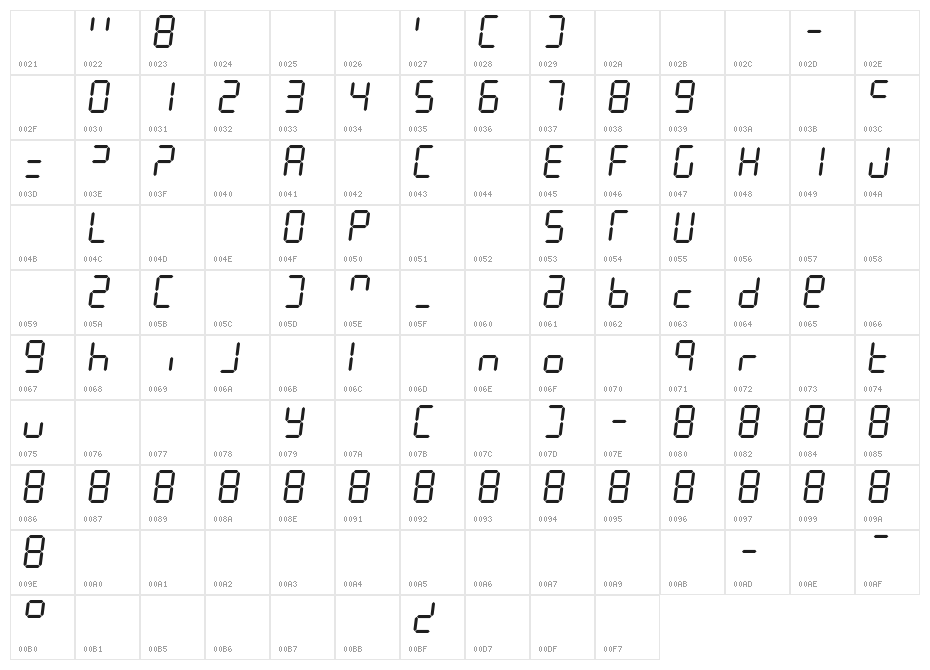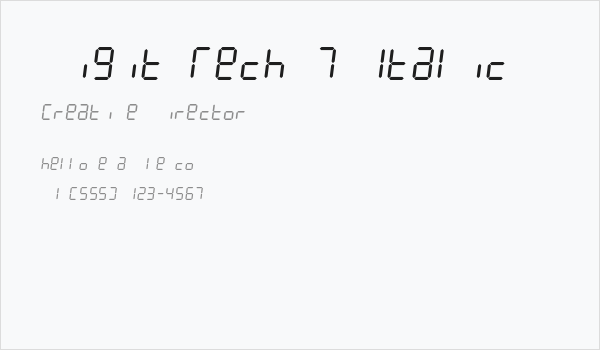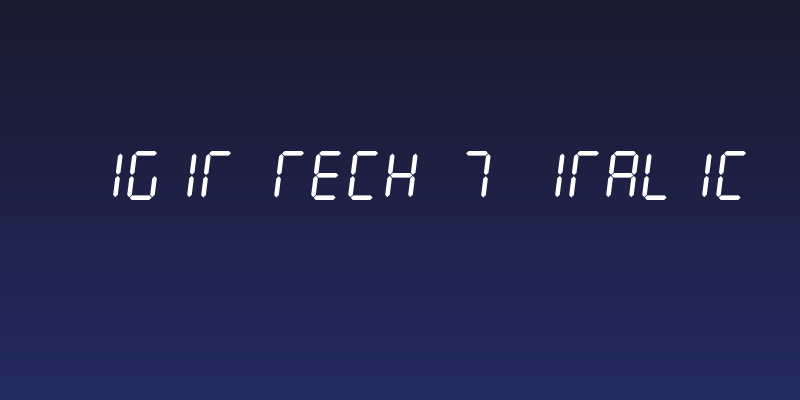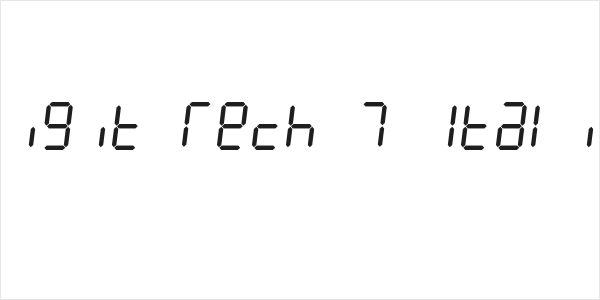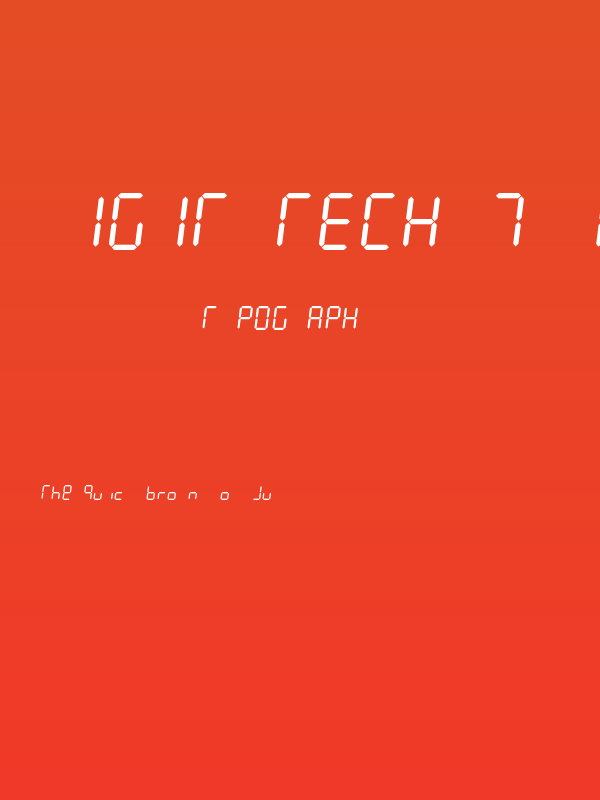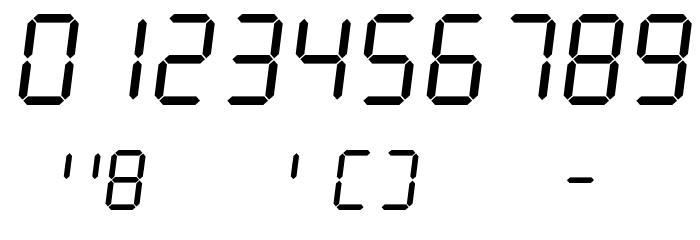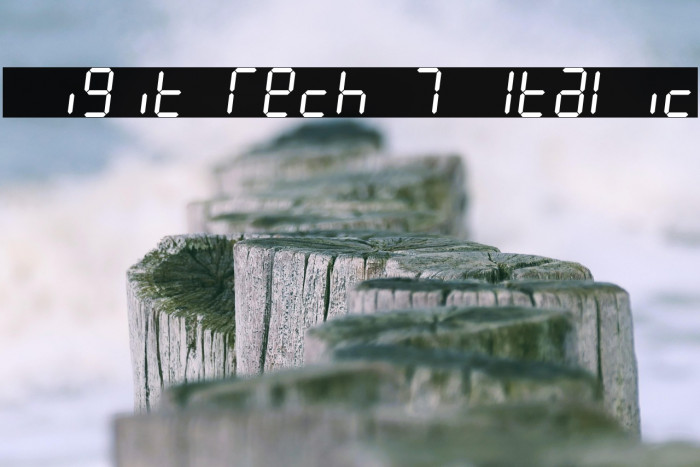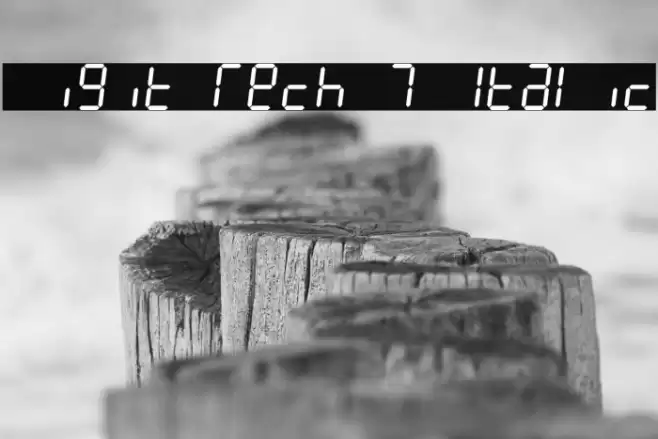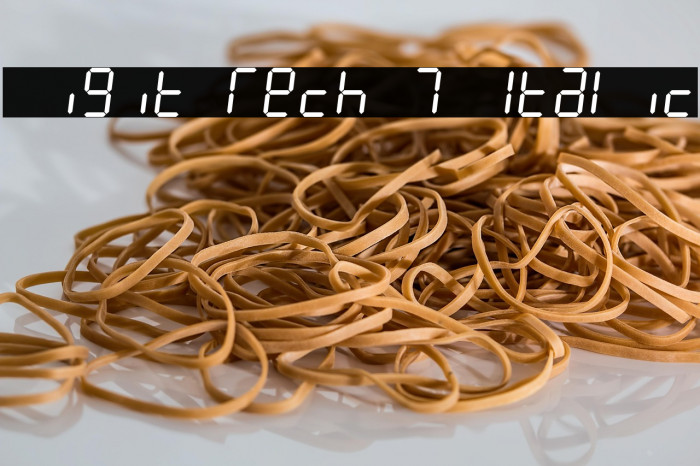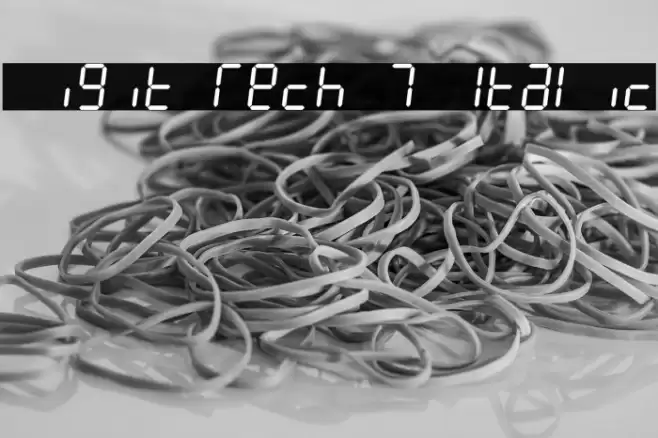
Digit Tech 7 Italic Font
✎ Futuristic
| الاسم | Digit Tech 7 Italic |
| عائلة الخط | Digit Tech 7 |
| Style | DigitTech7-Italic |
| الوزن | Italic |
| الفئات | Futuristic |
| مائل | Yes |
| تباعد الأحرف | Normal |
| حالة الاستخدام | Headlines, Digital displays, Tech interfaces |
| مشاريع مقترحة | This font is perfect for digital displays, tech-themed branding, futuristic posters, and user interfaces that require a modern, digital look. |
| عرض ثابت | Yes |